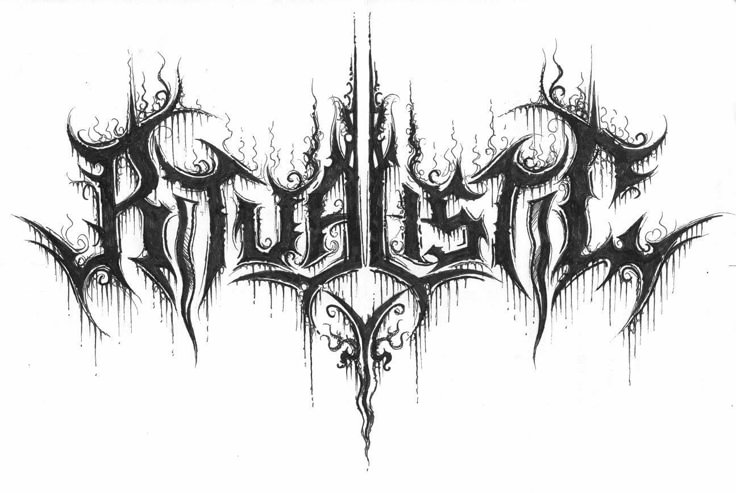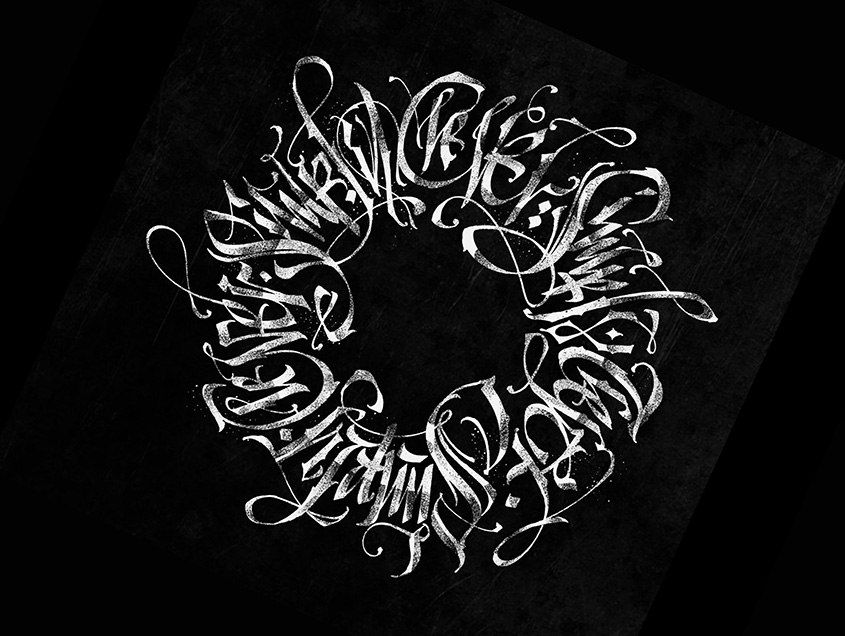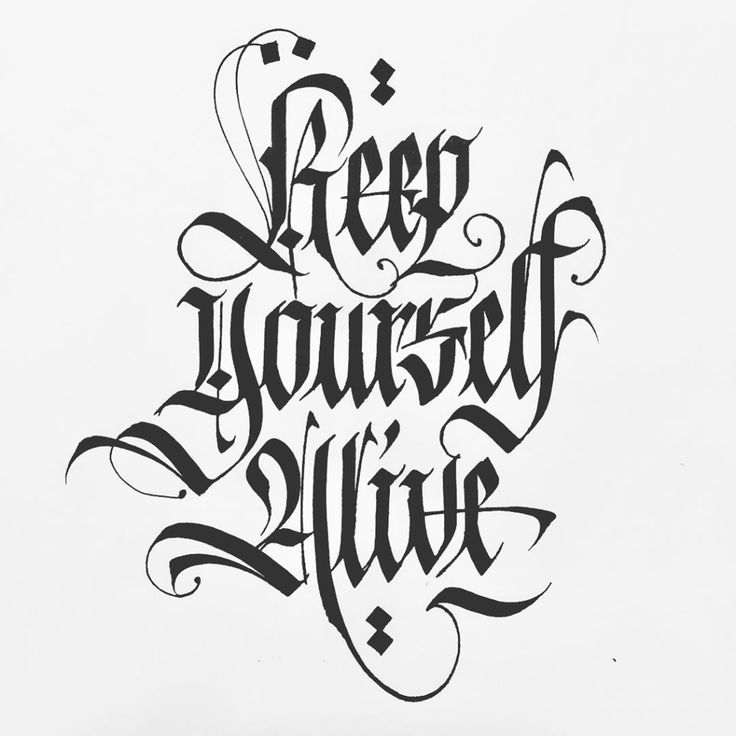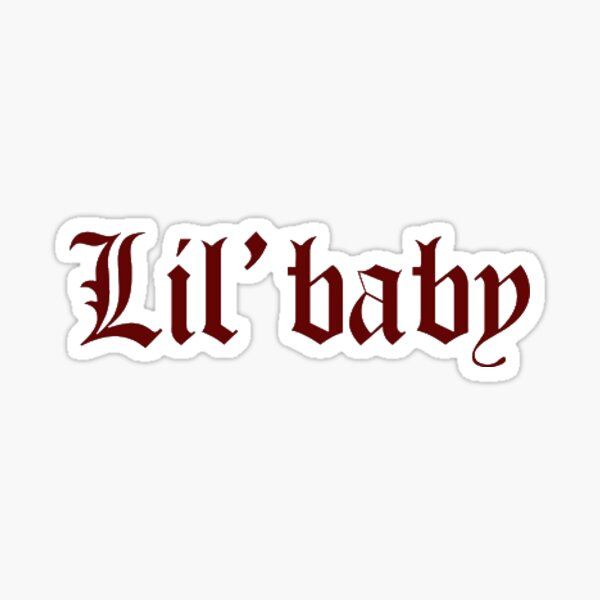
Загадочные готические тату надписи
Использование различных видов шрифтов является отдельным течением в искусстве тату. Его называют «Letters», что переводится просто — буквы. Но это не простые буквы, ведь от внешнего вида надписи и смысловой наполненности текста зависит многое. Готические надписи тату часто используются для нанесения на кожу знаменитых высказываний. Многим нравятся крылатые фразы на латыни или английском.
Сейчас все чаще готический стиль используется для тату с русскими буквами. Такой вид написания добавляет брутальности даже несерьезной фразе. Если молодой человек захочет сделать татуировку с именем любимой, то с помощью элементов готики надпись на коже можно выполнить очень мужественной и загадочной. Чаще всего готическое написание фраз для татуировок используют мужчины.
Но тату надписи
Это связано с увеличившейся в свое время модой на субкультуру готов. А также желанием девушек казаться более сильными и решительными, что хочется подчеркнуть татуировкой. Готика в тату — это не только специальный шрифт с рваными линиями, широкими штрихами и плотным написанием букв во фразах. Вы можете создать эскиз и распечатать его на принтере, а если закончился картридж, то заправка картриджей алматы поможет справится с этой проблемой. Все чаще средневековые персонажи становятся темой для нательных произведений искусства. Загадочные и агрессивные химеры, мрачные и демонические гаргульи становятся дополнением к шрифтам или отдельными персонажами для
Так как к современной готической субкультуре часто относят и вампирское направление, то часто рядом с тату готические надписи находят себе место на эскизе черные кошки или коварные вампиры.
Благодаря переосмыслению классических персонажей в готическом стиле могут изображаться Мэрилин Монро или даже Ленин.
Среди кибер-готов популярны татуировки с роботами и персонажами из готических аниме. Есть также отдельная категория
Нанесение готических надписей и изображений, на первый взгляд, не требуют высокого профессионализма мастера. Если серьезная фраза на коже «поплывет» через пару лет, это будет очень некрасиво. А банальная татуировка может быстро надоесть. Поэтому к выбору мастера и разработке эскиза нужно относиться очень внимательно.
Готические буквы — Татуировки и примеры, которые вдохновят вас ими
готические надписи татуировки это один из самых востребованных стилей. Некоторые тексты заставляют нас думать о довольно старых временах, которые оставили нам наследие в виде вдохновения. Настолько, что когда мы думаем о татуировке с буквами, большая часть ее будет иметь стиль, подобный тому, который мы показываем вам сегодня.
Однажды готические буквы, которые будут выбраны составить наш дизайн, нам придется сделать второй шаг. Это имя собственное? А может, выберем оригинальную и глубокую фразу? Без сомнения, есть несколько вариантов, которые стоит рассмотреть, и все они дают более чем потрясающий результат.
Готические буквы для имен собственных
татуировки с собственным именем Они очень распространены. В них некоторые люди решают принести свои собственные, хотя мы также видели, как этот особенный человек может быть главным героем. Всегда советуют, что если вы собираетесь сделать татуировку с именем вашего партнера, это нечто более чем серьезное. Это не первый случай, когда кто-то татуирует имя своего парня или девушки, и вскоре после этого им приходится менять его или прикрываться.
Как бы то ни было, когда мы выбираем имя, оно должно нести в себе много символики. Родители и другие семьи — хороший вариант для ношения на нашей коже. Все они могут быть татуированные как заглавными буквами, которые действительно используются чаще всего, когда мы говорим о готических буквах, но также и в нижнем регистре.
Таким же образом вы можете дополнить каждое имя простым следом. В этом случае он всегда делается черными чернилами, чтобы добавить оригинальности, присущей готической моде.
Татуированные фразы готическими буквами
Если вы думаете, что одного слова недостаточно, вы всегда можете прибегнуть к фразам. Сначала подумаем, где их носить. Это самая важная вещь, так как это повлияет на длину предложения. Вот почему многие люди выбирают делают татуировку на руках, когда выбирают длинную фразу. Предплечье — обычно одна из самых востребованных областей. Конечно, спина не отстает.
Вдобавок мы еще раз видим, как дизайны продолжают нас удивлять. Некоторые из них имеют оттенок, который усиливает каждую из букв, однако другие переносят его на самый тонкий ландшафт, оставляя более тонкие буквы, но всегда с большой оригинальностью. Если хочешь привлекательные и украшенные татуировки, мы помечаем дизайн как контуры, которые могут исходить от части букв или с фоном.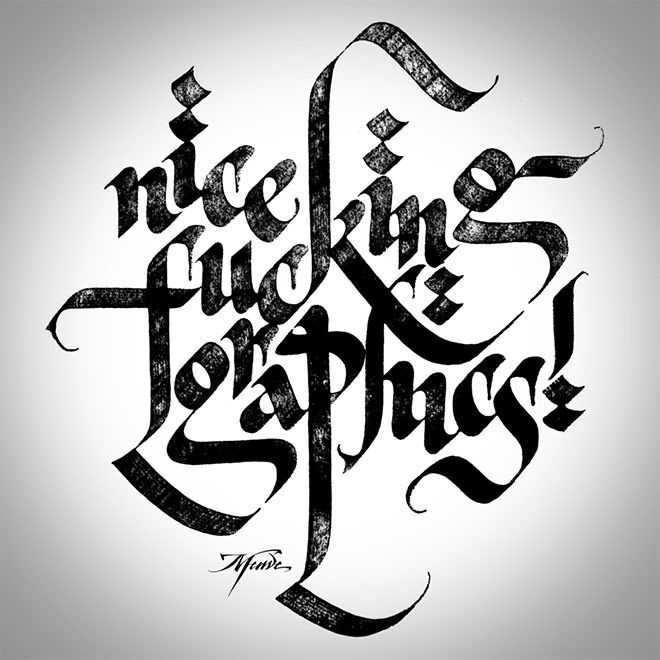